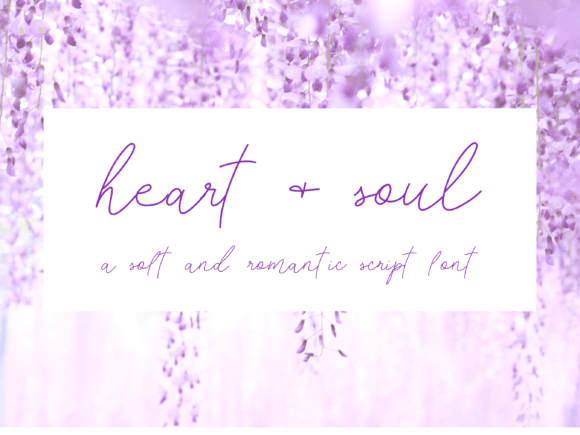
Heart + Soul
Heart + Soulのような高品質の素材をお探しの場合、このプレミアムパッケージはクリエイティブなプロジェクトに素晴らしい選択です。
POD(オンデマンド印刷)製品、結婚式の招待状、またはソーシャルメディアのグラフィックを作成している場合でも、Heart + Soulは理想的です。